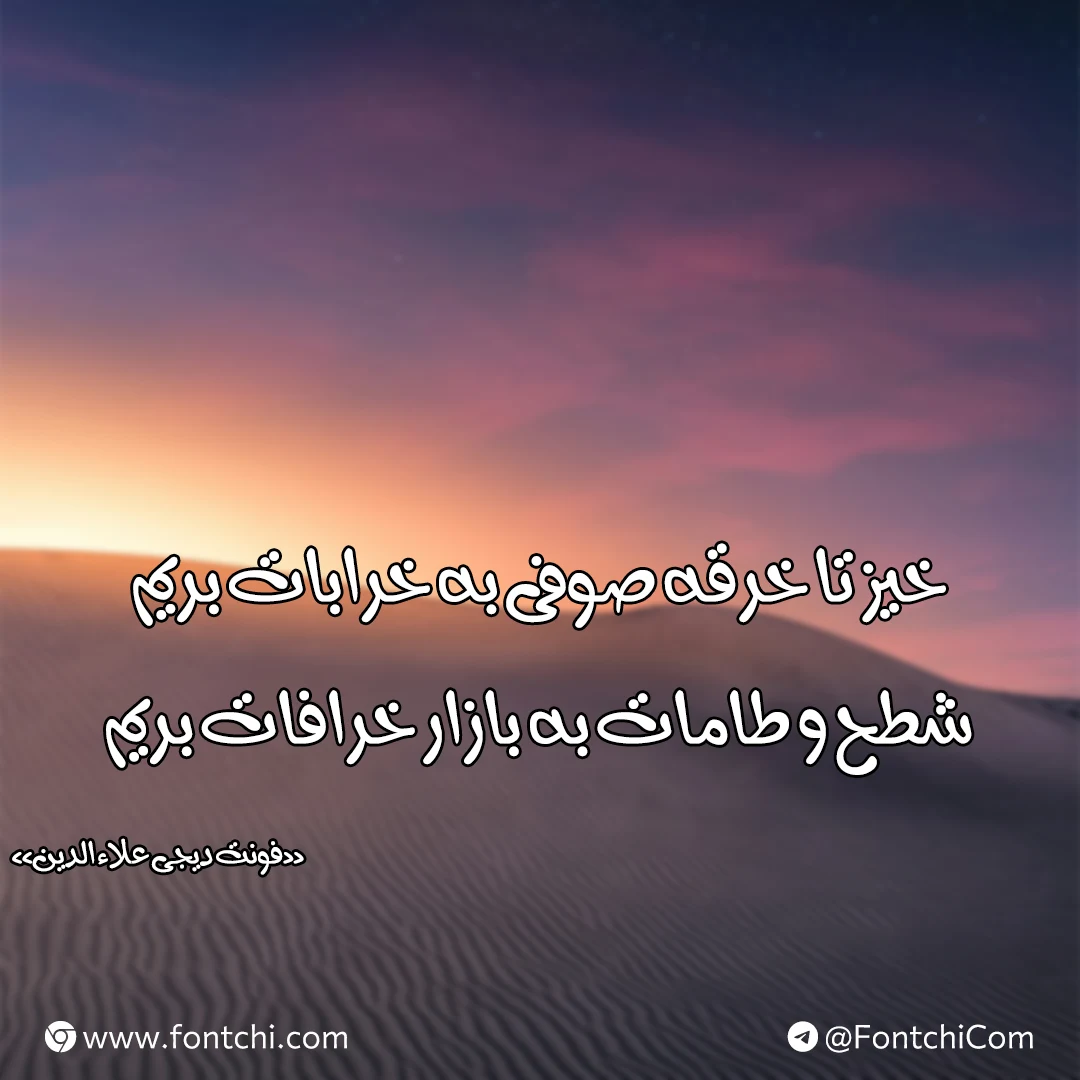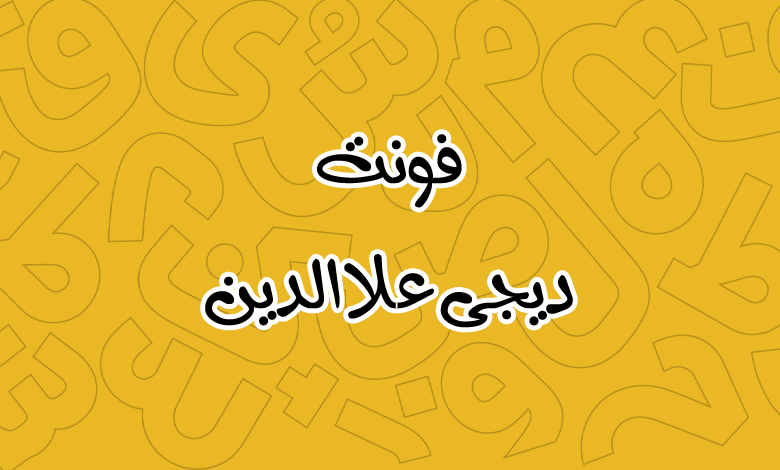
فونت دیجی علاالدین (Digi Aladin)
| نام | دیجی علاالدین |
| نام نمایشی | Digi Aladin |
| طراح | مهدی برقگیر |
فونت دیجی علاالدین (به انگلیسی: Digi Aladin) از فونتهای دستنویس و فانتزی رایگان است که با یک وزن بولد ارائه شده و برای پروژههای گرافیکی و متون کوتاه مناسب است. ساختار حروف در این فونت ظاهری صمیمی دارد که میتوان در صنعت چاپ و مطبوعات برای جلد عنوان کتاب و مجلات، بهویژه در حوزه کودک و نوجوان از آن استفاده کرد.
این فونت رایگان فارسی توسط مهدی برقگیر طراحی شده که از زبانهای فارسی، عربی، کوردی و انگلیسی به خوبی پشتیبانی میکند. در ادامه با بررسی این فونت همراهتان هستیم.
فونت علاالدین با طراحی دستنویس و حالوهوای شاد و پویا، شخصیتی فانتزی و شیک دارد که آن را از فونتهای رسمی متمایز میکند. این فونت با الهام از دستخط طبیعی و با اضافه کردن جایگزینهای هوشمند و اعرابگذاری استاندارد طراحی شده است.
با طراحی شاد و فانتزی خود، بهخوبی توجه مخاطب را جلب میکند و برای پروژههایی که نیاز به جلوههای بصری خلاقانه دارند، بسیار مناسب است.
این فونت به دلیل طراحی فانتزی و تزئینی، کاربردهای زیادی دارد؛ از جمله:
- طراحی گرافیکی: پوسترها، تراکتها، جلد مجلات و لوگوتایپ.
- شبکههای اجتماعی: استوریها و پستهای اینستاگرامی با تمهای عاشقانه، فانتزی و آموزشی.
- تایپوگرافی وب: برای عناوین و بخشهای تزئینی در طراحی وبسایت
علاوه بر زبان فارسی، از زبانهای کردی و عربی پشتیبانی میکند، که این ویژگی آن را برای کاربرانی که به چندزبانگی نیاز دارند، مناسب میسازد. همچنین برای زبان انگلیسی نیز گلیفهای حروف با همان سبک نسخه فارسی را دارد. تنها کاستی این فونت در بخش اعداد است که برای عدد ۶ فارسی و عربی از یگ گلیف مشترک عربی استفاده شده است.
با این حال به دلیل ماهیت فانتزی و تزئینی، این فونت برای متون طولانی و رسمی مناسب نیست و ممکن است در چنین کاربردهایی خوانایی کمتری داشته باشد. در حالی که برای متون کوتاه و عناوین گزینهای عالی محسوب میشود.